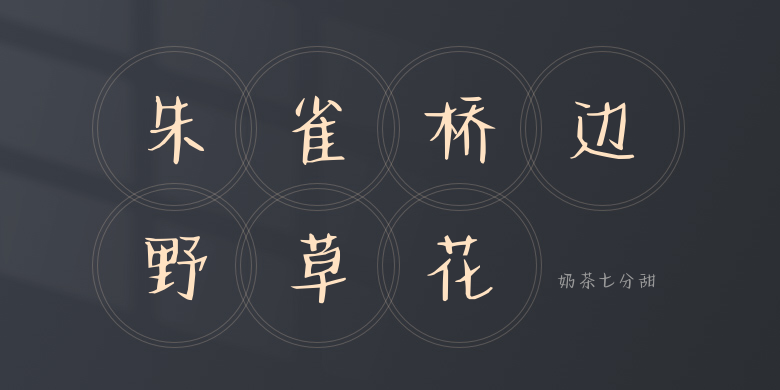
奶茶七分甜
奶茶七分甜,这款字体结构工整、笔画清晰,兼顾美观与易读性,适用于标题、正文、海报、包装、LOGO 等多种场景。字形优雅稳定,风格百搭耐看,适配日常排版与创意设计,让文字呈现更舒适、更具质感。奶茶七分甜一笔一画,皆是细节,以均衡的比例、流畅的线条打造舒适视觉体验,字形端正大气,风格简约现代。无论是商业设计、品牌宣传还是日常排版,都能轻松驾驭,让文字更有格调与力量。奶茶七分甜字体下载。